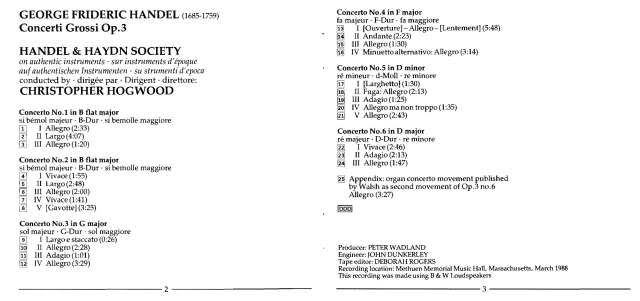
für ein booklet einer Audio-CD suche ich einen Font, der die Zahlen in rechteckigen Kästchen besitzt, um die Track-Nummern fortlaufend aufzuführen.
Weiß jemand, welcher Font das hat?
ja, das ist doch schon mal eine Auswahl! Die DecoNumbers Square wäre die passendste.
Die Bundesbahn hat ja leider nur die Zahlen 1 bis 9, die wäre sonst auch nicht schlecht.
Hmm, für die meisten Anwendungen kann man doch jeder beliebigen Schrift, z.B. in ID ein "Kästchen"-Format zuweisen …
"Kästchen"-Format
Was ist denn ein Kästchen-Format?
@Jens - der erste Link ist, was ich suche.
@bertel - diese Zusammenstellung hatte ich inzwischen auch schon gefunden. Die für mich passendste aus der Liste scheint mir auch die aus dem Link von Jens zu sein.
Was ist denn ein Kästchen-Format?
Deine eigenen Kästchenzahlen kannst Du zum Beispiel so erzeugen: In InDesign einen Rahmen in gewünschter Größe aufziehen, Deine Zahl hineinschreiben, Größe und Schriftart wählen, die Zahl exakt mittig platzieren (mittelachsiger Satz und eine Leerzeile gewünschter Größe über die Zahl setzen) und dann dem Rahmen und der Zahl die Farben Deiner Wahl zuweisen – fertig. Das so erzeugte Zahlenkästchen kannst Du sogar mittels Copy-and-paste in einen Fließtext einfügen, so dass es mit diesem läuft.
>Neenee, keinen Extra-Rahmen! Hinterlegte Texte lassen sich auch mit der Unterstreichungsoption (Zeichenformat) oder Absatzlinien (Absatzformat) ganz sauber umsetzen
… ich dachte die Formatierung einer farbl. Hinterlegung etc. wären bekannt.
Das ist sie auch, nur liefert das zum einen keine Kästchen und zum anderen ist die Hinterlegung immer der Zahlenbreite angepasst. Das wird aber beides nicht gewünscht sein …
Bei der von mir geschilderten Methode hat man für die Kästchen und ihre Rahmen, so wie deren Seitenverhältnisse alle Gestaltungsmöglichkeiten, die man sich wünscht. Das ist ja manchmal auch nicht unwichtig. :-)
Eigentlich sollte das Kästchen ein Rahmen sein, das hatte ich nicht deutlich genug ausgedrückt. Ein Font ist gefunden - und es passt wunderbar.
Aber für eine farbige oder graue Hinterlegung ist die Absatzlinie natürlich sehr praktisch.
Ein Rahmenkästchen-Format - das wär noch mal was ...
… (mittelachsiger Satz und eine Leerzeile gewünschter Größe über die Zahl setzen)
Nur aus Interesse (ich habe keine Zeit das so schnell nachzuabauen): warum brauchst Du die Leerzeile? Kannst Du das nicht besser über einen Grundlinienversatz justieren und damit gleich im Zeichenformat verankern? :-?
Klar, es führen ja immer mehrere Wege zum Ziel. :-D Ich hatte das mit dem Kästchen auch nur ganz auf die Schnelle mal für GePix ausprobiert und den möglichen Lösungsansatz aufgeschrieben. Jeder Verbesserungsvorschlag ist herzlich willkommen.
Diese Beschränkungen sind das, was mich an InDesign im Vergleich zu CSS stört. Naja, dafür geht anderes besser.
was für berschränkungen?
man kann doch beliebige form erstellen und die zum textfeld deklarieren, ob sie jetzt mit farbe gefüllt ist oder nur eine outline als kontur hat (ist damit ein »kästchen« gemeint?).
ich verstehe das problem nicht und schon gar nicht den grund im diesem fall (cd-cover) nach einer schrift die das hat zu suchen?
Hier ein Beispiel zum Verständnis:
Die Vorschläge, wie man das basteln kann, waren mir zu tüddelig für mein Vorhaben ...
ah - du verstehst das Problem nicht, weil du eine einfachere Lösung weißt.
Verstehe ... ;-)
Aber mir schienen die angebotenen Lösungen zu umständlich, ohne es - ich gebe es zu - ausprobiert zu haben. Vielleicht hast du recht, aber mich schreckten die 8 Spalten mit den Track-Angaben für insgesamt 6 CDs. Da war mir ein Font und Klick auf die Zahl die einfachste Lösung ...
anyway - es ist vollbracht.
für die zukunft, falls du mehr als ein kästchen brauchst, z. b. ein stern :lol:
die lösung die kathrin oben beschrieben hat ist letztendlich nach dem man es schnell ein mal erstellt hat auch nur ein klick und die zahl ändern, du hast aber volle kontrolle über die wahl der schrift.
Mhh, das ist dann wohl wirklich Geschmacksache. Für mich wären solche im Textfluss eingebetteten Objekte die allerletzte Wahl, da ich die nicht in jeder Hinsicht global steuern kann. Dann ist das immer irgendwie »hingefummelt«. Die oben gezeigten Beispiel hätte ich dann mit Tabellen umgesetzt, wenn ein Font verboten gewesen wäre.